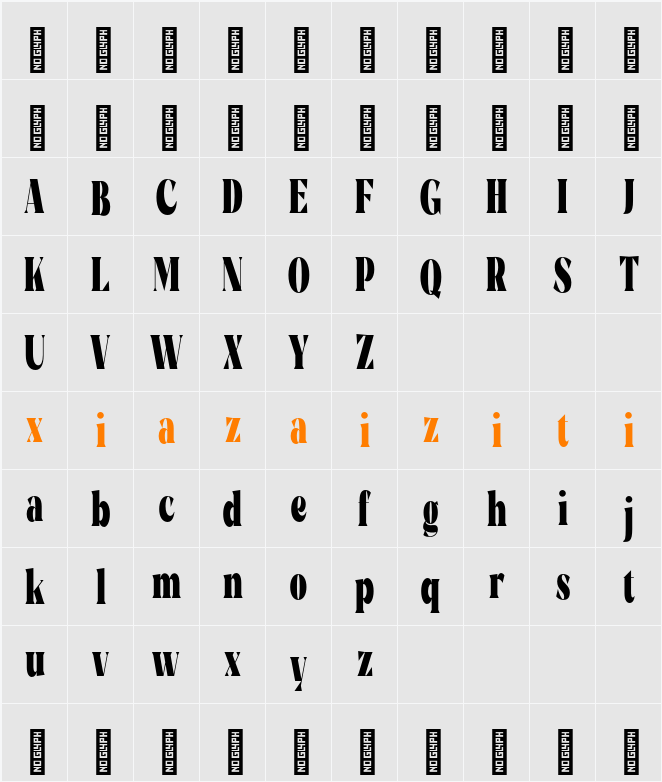
Rigam Condensed
Rigam Condensed,这款字体结构工整、笔画清晰,兼顾美观与易读性,适用于标题、正文、海报、包装、LOGO 等多种场景。字形优雅稳定,风格百搭耐看,适配日常排版与创意设计,让文字呈现更舒适、更具质感。Rigam Condensed一笔一画,皆是细节,以均衡的比例、流畅的线条打造舒适视觉体验,字形端正大气,风格简约现代。无论是商业设计、品牌宣传还是日常排版,都能轻松驾驭,让文字更有格调与力量。Rigam Condensed字体下载。
• 制造商: Fitrah Type
• 设计师: Moch Fitrah Hidayat